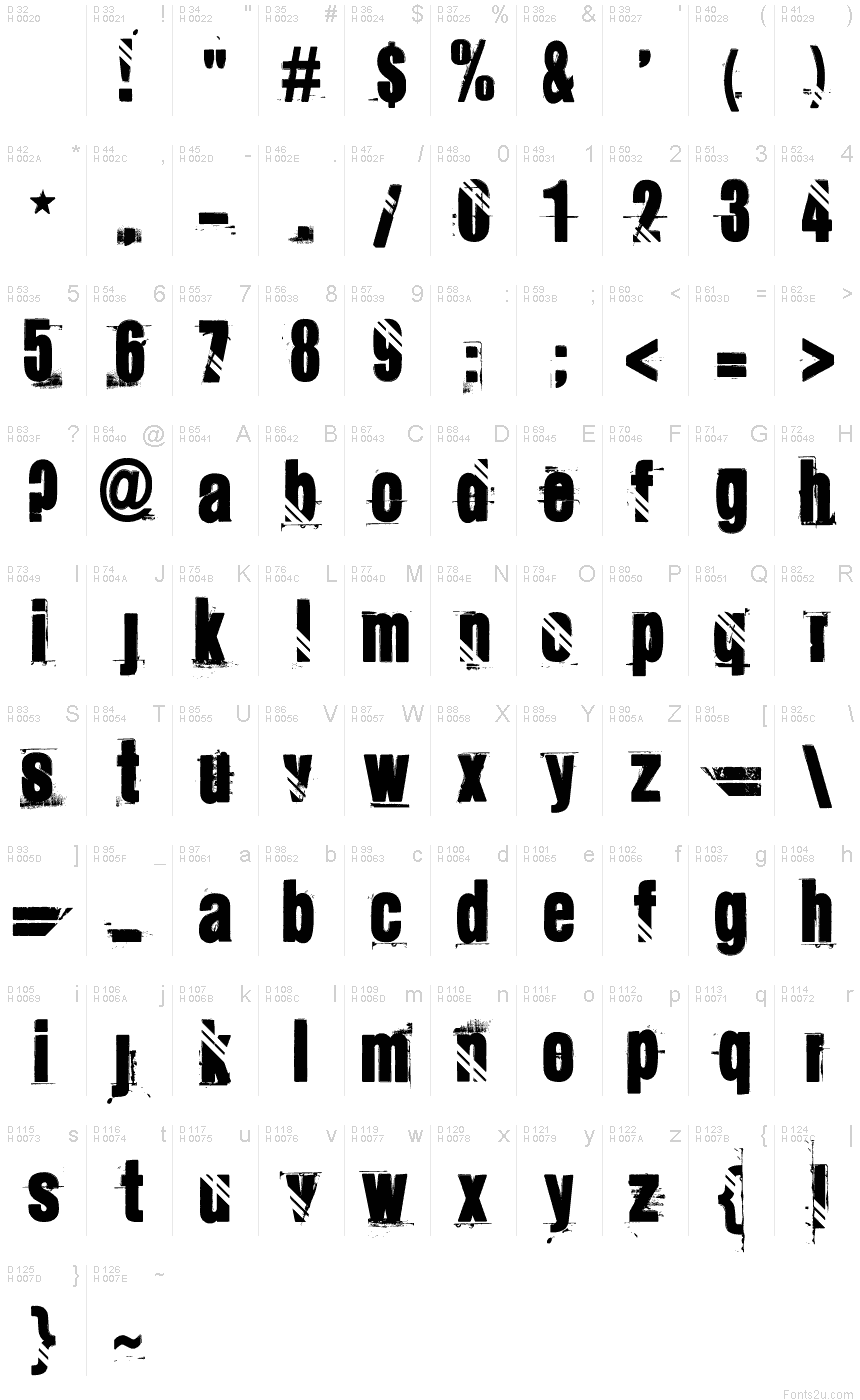
Olympiques od Last Soundtrack to darmowy, erodowany font typu display o surowej, dynamicznej energii, która przywodzi na myśl kserowane plakaty i zdrapaną grafikę uliczną. Litery są wysokie, ciężkie i nierówno sfatygowane, z poszarpanymi krawędziami, nagłymi ubytkami i kilkoma ciętymi przerwami, dzięki czemu napis sprawia wrażenie wciśniętego, odciśniętego i lekko uszkodzonego.
Ta ziarnista tekstura sprawia, że jest to naturalny wybór na ulotki koncertowe, okładki zinów, grafikę skejtową, okładki albumów i krótkie tytuły, gdzie liternictwo samo w sobie nadaje charakteru. Jako darmowy font, świetnie sprawdzi się w wyrazistych nagłówkach, eksperymentach z logo i szybkich projektach brandingowych, które wymagają szorstkiego, miejskiego głosu, a nie wygładzonego wykończenia.